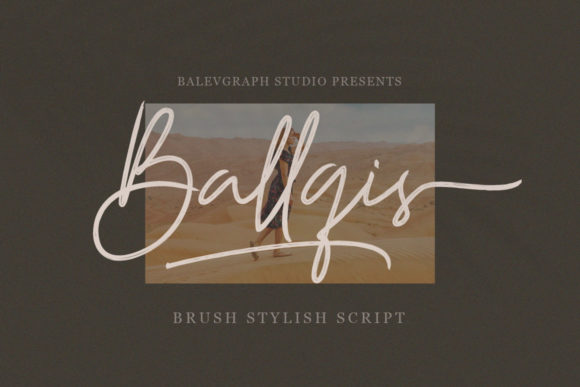
Название: Ballqis Font (2021)
Ballqis - это плавный, стильный и аккуратный рукописный шрифт.
Этот универсальный шрифт имеет широкий спектр применения - от поздравительных открыток до заголовков - и гарантированно придаст романтический настрой вашему следующему проекту.